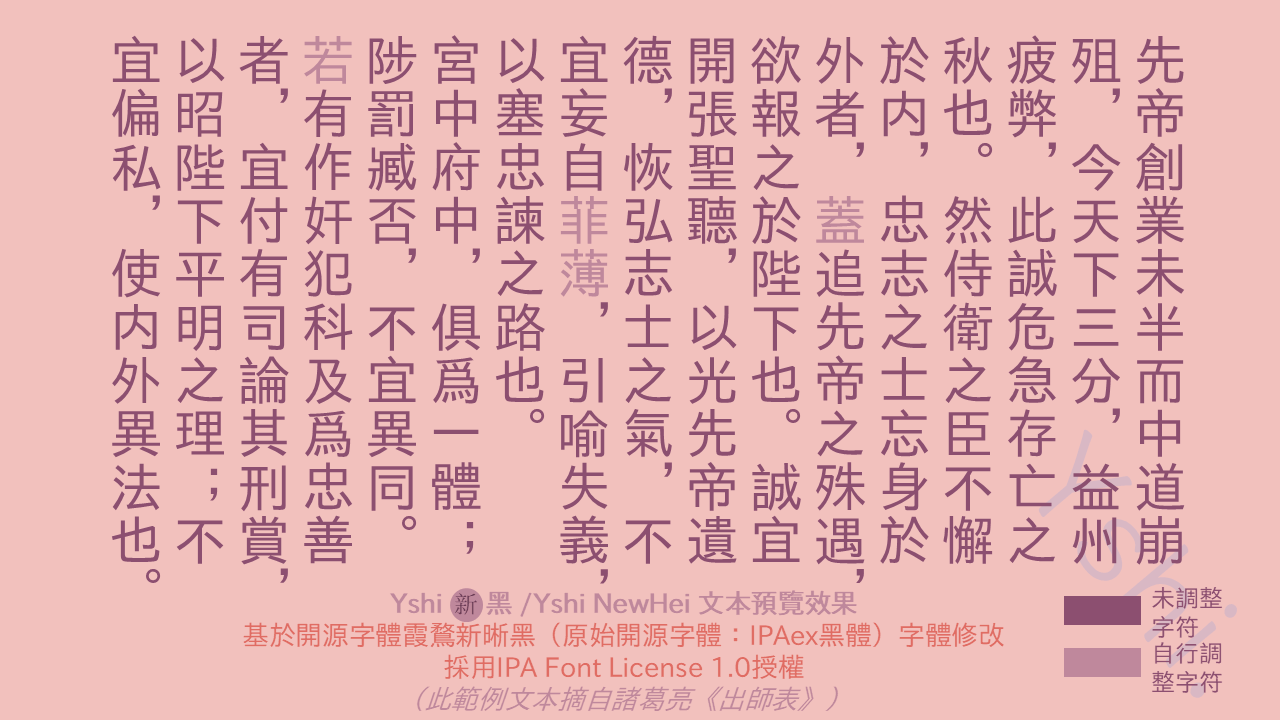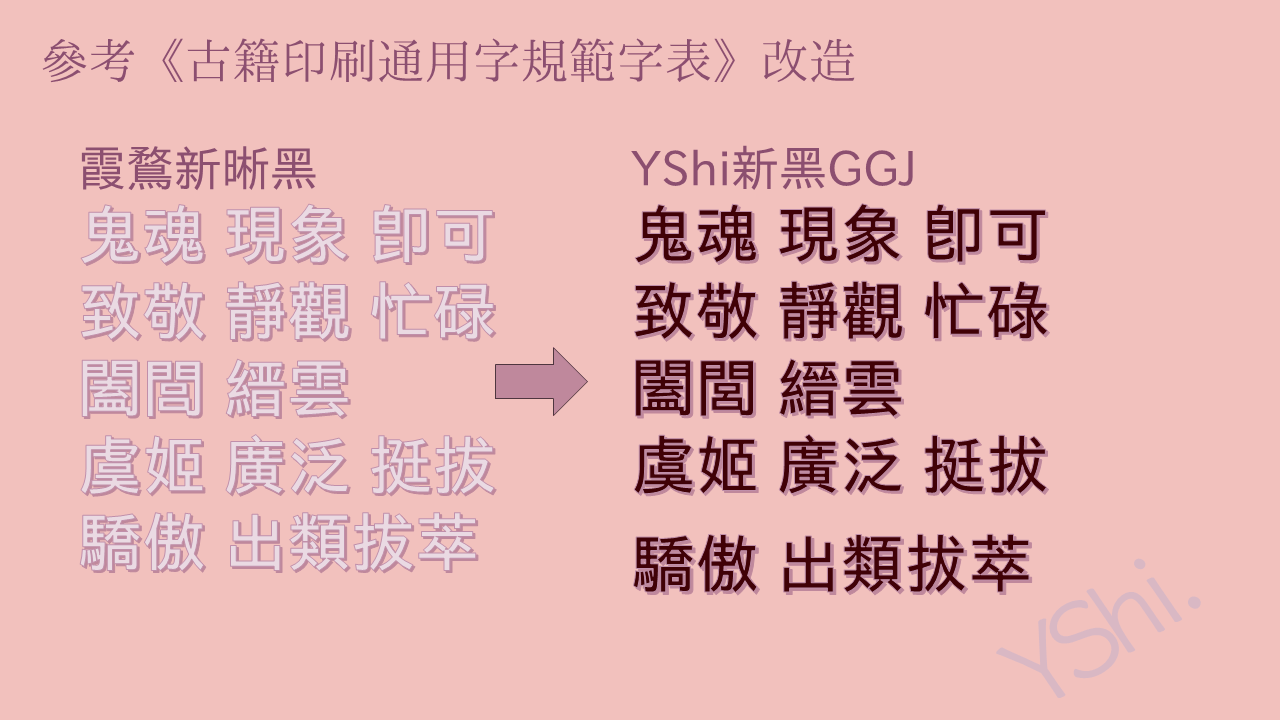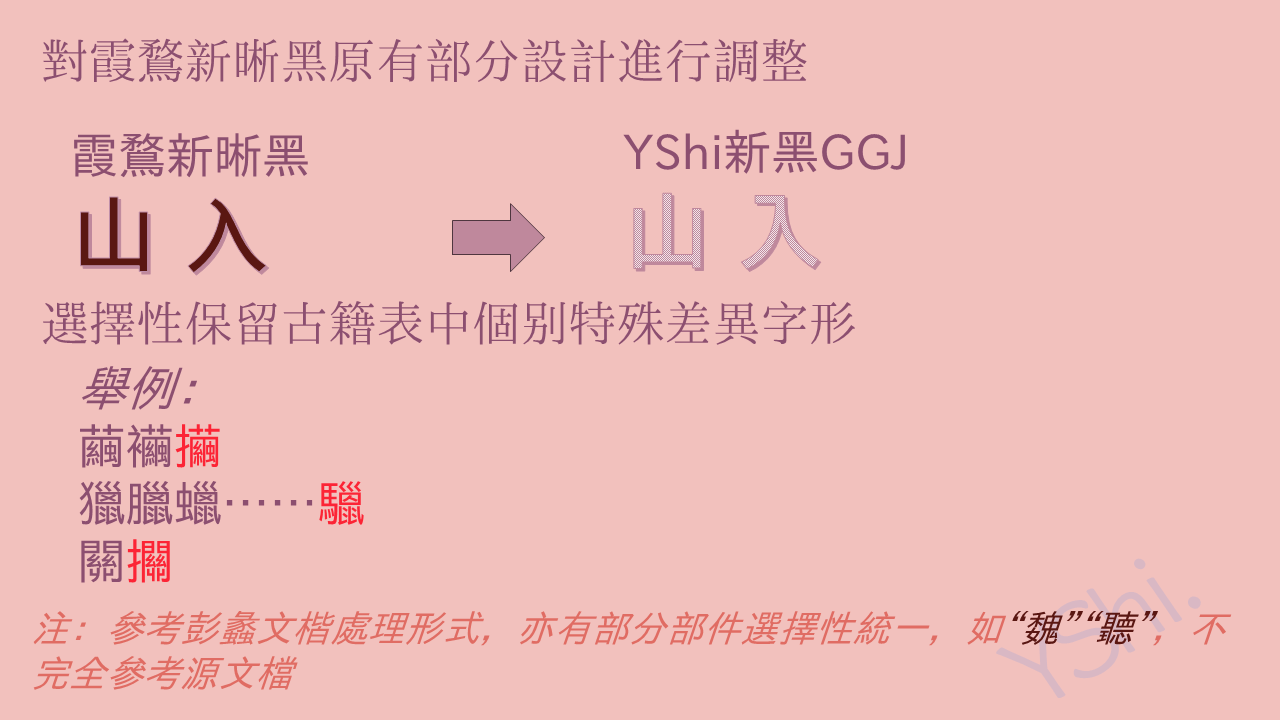
本字体是在IPAex黑体、霞鹜晰黑、霞鹜新晰黑等现有字体的基础上进行改编与补全而成的,其核心目标是致力于完善《古籍印刷通用字规范字表》所涵盖的字形,以满足古籍整理、数字化出版及学术研究领域对规范、完整字形的需求。针对《规范字表》中收录但在主流数字字体中存在缺失或形态不一的汉字,本字体进行了系统性的收集、整理与重绘,力求在统一风格的前提下,提供准确、可靠的字形支持。
展示Yshi新黑字体的文本预览效果,基于开源字体霞鹜新晰黑修改,采用IPA Font License 1.0授权。示例文本摘自诸葛亮《出师表》。
显示将霞鹜新晰黑字体修改为YShi新黑GGJ字体的对比,参考古籍印刷通用字规范字表进行改造。
展示“霞鶩新晰黑”与“YShi新黑GGJ”字体的对照调整示例,包括“山入”等字形的对比,以及选择性保留的特殊差异字形。